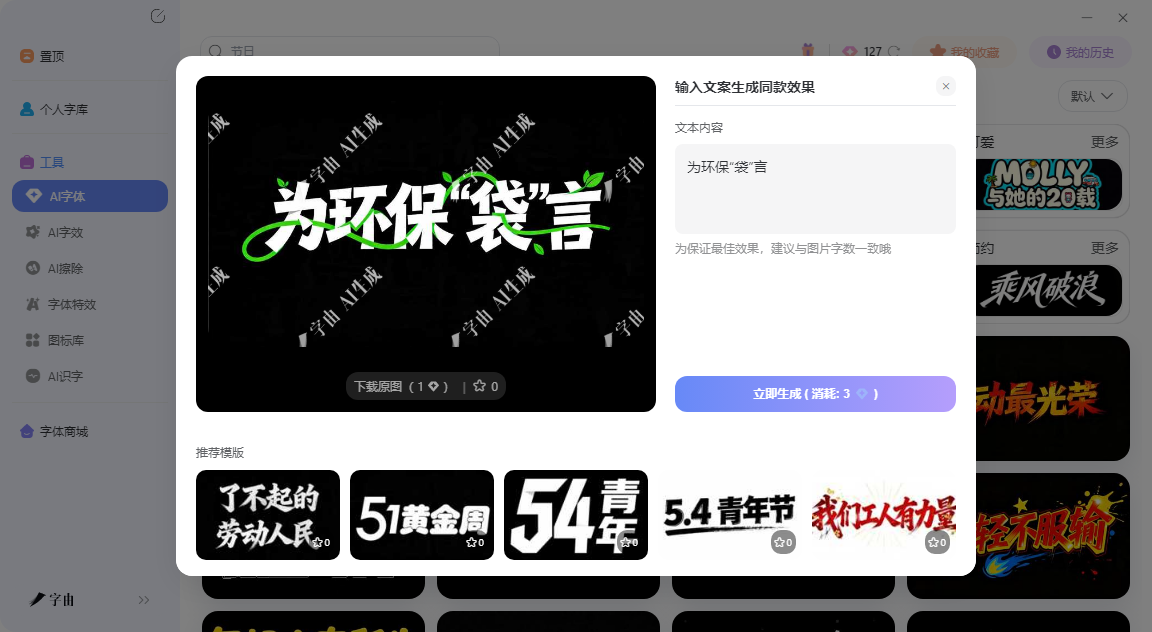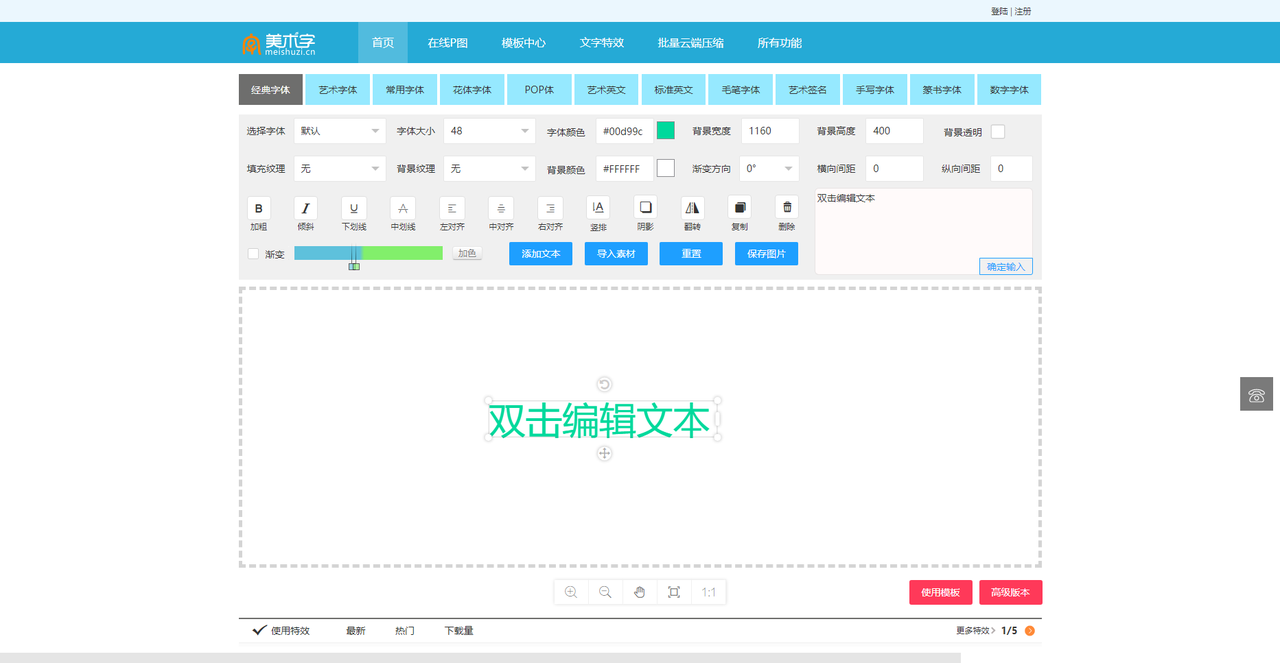
字体转化器哪个好?实测5款在线工具,输入文字秒变特效
你有没有过这种经历:微信朋友圈想发一句花体字,结果只能打普通宋体;做海报标题想要霓虹灯效果,打开PS调了半天还是土;给游戏账号改个昵称,翻来覆去只有字母和数字。其实这些问题,一个字体转化器就能搞定——输入文字,选个样式,复制粘贴或者下载图片,几秒钟完事。今天我来给大家实测了5款字体转化工具,从AI一键生成到参数自由调节,从海量场景模板到正版字体库,覆盖了各种使用场景。喜欢的可以下滑查看。
市面上很多字体转化器,生成的是Unicode花体字(只能复制粘贴纯文本),或者低像素的免费模板图。但如果你做的是商业海报、品牌物料,需要高清、可商用、有设计感的艺术字图,大多数免费工具都不够用。
字由的AI字体功能解决的就是这个问题。它不是让你从零开始调参数,而是直接给你由专业设计师做好的字体特效模板。打开字由客户端,在“AI工具”下找到“AI字体”,左侧筛选栏里按场景和风格分类:国潮风、霓虹灯、金属质感、手写书法、电商促销、科技感……每个分类下面都有几十款模板。
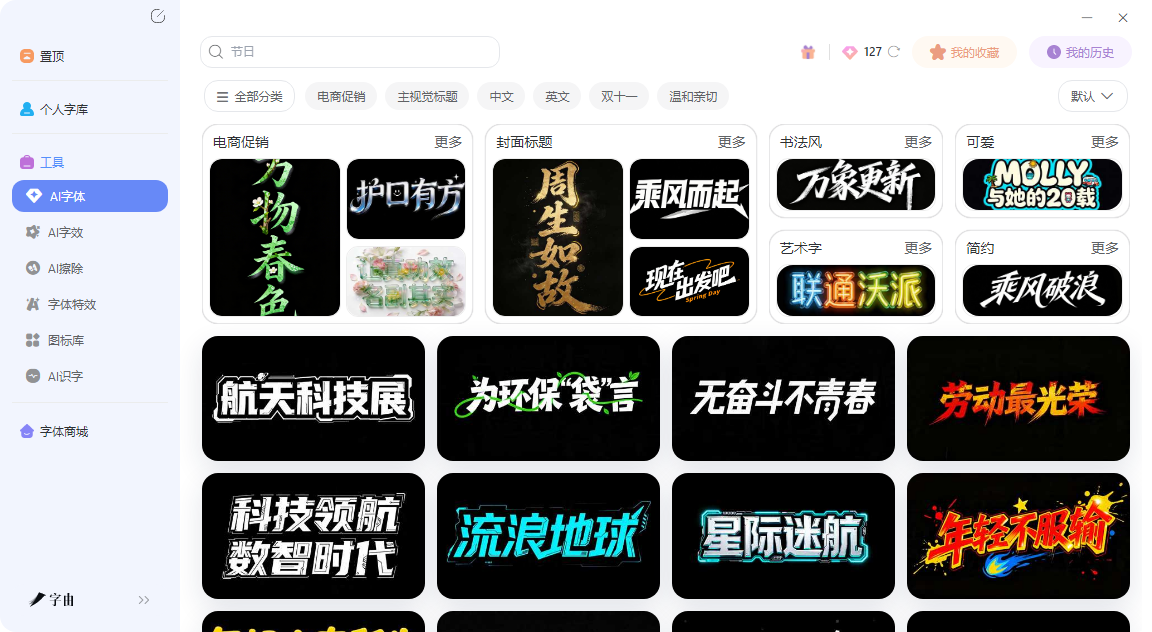
假设你正在做一张奶茶店的夏季促销海报,标题是“杨枝甘露”。你想让标题有点国潮感,但自己不会设计。打开字由AI字体,点“国潮风”分类,翻到一款水墨晕染效果的模板,点击“做同款”,在右侧输入框把模板里的文字换成“杨枝甘露”,点“立即生成”。10秒后,一张带有水墨书法效果的艺术字图就出来了。下载透明背景的PNG,直接拖进海报里。整个过程不到一分钟。
2、美术字
第二个工具叫美术字。它和字由的“选模板”思路不同,更像一个简化版的PS文字工具,但操作更直观。打开页面,你可以输入文字,然后从左侧选择字体(经典字体、艺术字体、花体字体、POP体等),调整字体大小、颜色、背景宽度/高度、背景透明、填充纹理、背景纹理、渐变方向、横向/纵向间距等参数。还支持加粗、倾斜、下划线、中划线、左/右对齐、竖排、翻转、复制、删除、渐变、加色等操作。
如果你对艺术字的效果有比较具体的要求——比如颜色必须和品牌色一致、需要加渐变背景、文字要旋转某个角度——美木字的参数面板能让你精确控制。它比PS简单,又比普通生成器灵活。保存图片前可以实时预览,调整完直接下载。对于经常做海报、封面、Banner的设计师来说,这个工具能省掉不少在PS里调图层样式的时间。
3、猫眼艺术字
第三个工具是猫眼艺术字。它的特色是内置了大量中文字体预设,比如“凉如三月”“暴走梗漫”“月亮船”“墨香古意”等。输入文字后,可以从下拉菜单里快速切换字体,实时看到效果。同时支持调节字体大小、颜色、背景色、加粗、投影、斜体、下划线、旋转角度、图片尺寸、左右上边距、颜色渐变。页面下方还有一个“字体预览”区,列出了“你是我的”“暴走梗漫”“一起去看海”“凉如三月”等多种预设效果,点击就能快速切换到对应的字体样式。这个设计对选择困难症患者很友好——你不需要知道字体名字,看哪个预览图顺眼,点一下就能用在自己的文字上。亮点:支持“动态文字”和“在线生成艺术字”功能,还集成了文字logo设计、电子签名生成、印章在线生成器等附加工具。如果你偶尔需要做个签名或者印章,不用单独找工具了。
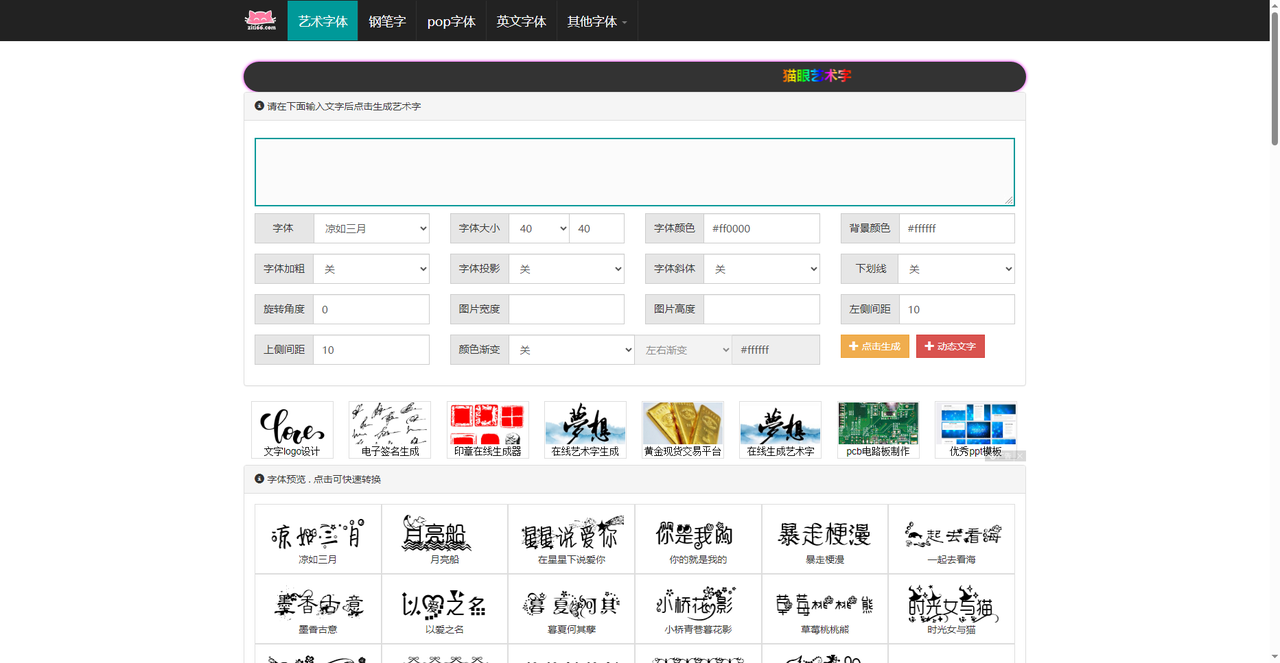
4、在线字体转换器
第四个网站是一个综合型的在线字体转换器。它的最大特点是分类细致,按使用场景做了筛选:虎年精选字体、海报字体下载、电商广告专用字体、书法字体、花体、简约字体、节日专属字体、卡通可爱字体等。还提供了“热门免费字体”推荐和“站长推荐”板块。这个站还集成了手工签名设计功能,输入姓名可以生成连笔签名、花式个性签、国风签名。在线转换器部分,可以选择字体(如“包图相体”“字语软糖体”“沧澜楷体”“南构帅芳超行书”等),调节大小、颜色、背景是否透明,点击“开始转换”就能生成图片。
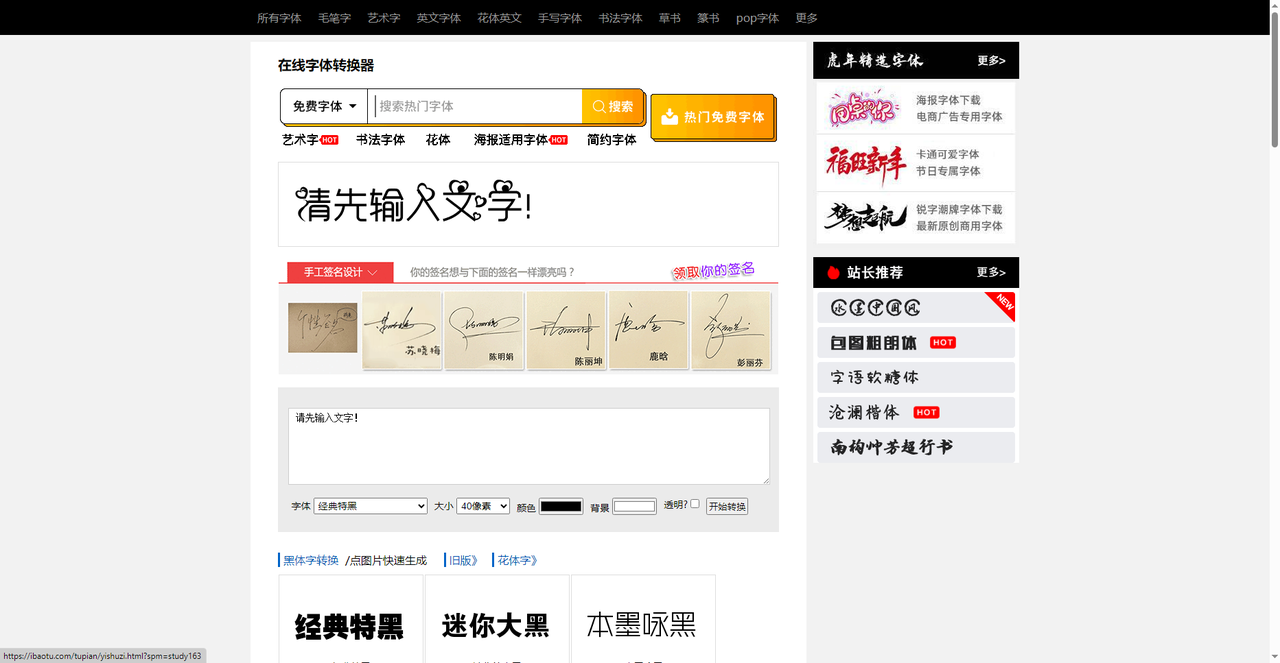
5、熊猫办公